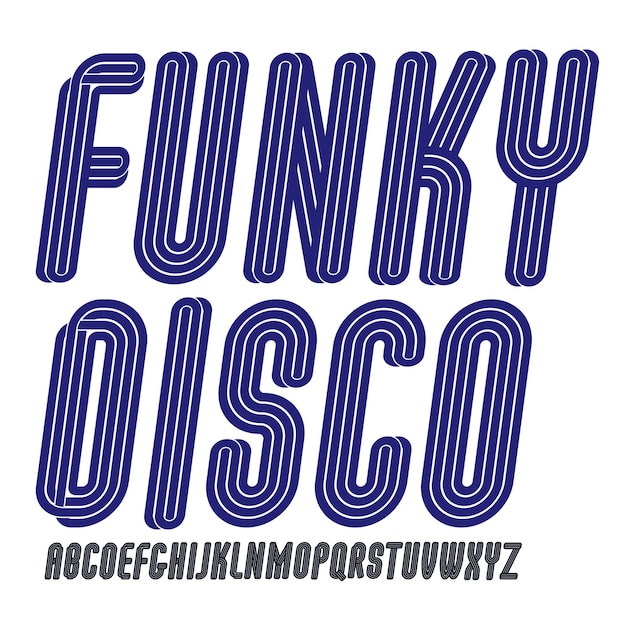
Набор заглавных букв алфавита диско-вектора изолирован. Модный сжатый шрифт, шрифт от а до я может быть использован при создании плаката. Создан с использованием геометрических тройных полос.Набор заглавных букв алфавита диско-вектора изолирован. Модный сжатый шрифт, шрифт от а до я может быть использован при создании плаката. Создан с использованием геометрических тройных полос.
Набор заглавных букв алфавита диско-вектора изолирован. Модный сжатый шрифт, шрифт от а до я может быть использован при создании плаката. Создан с использованием геометрических тройных полос.